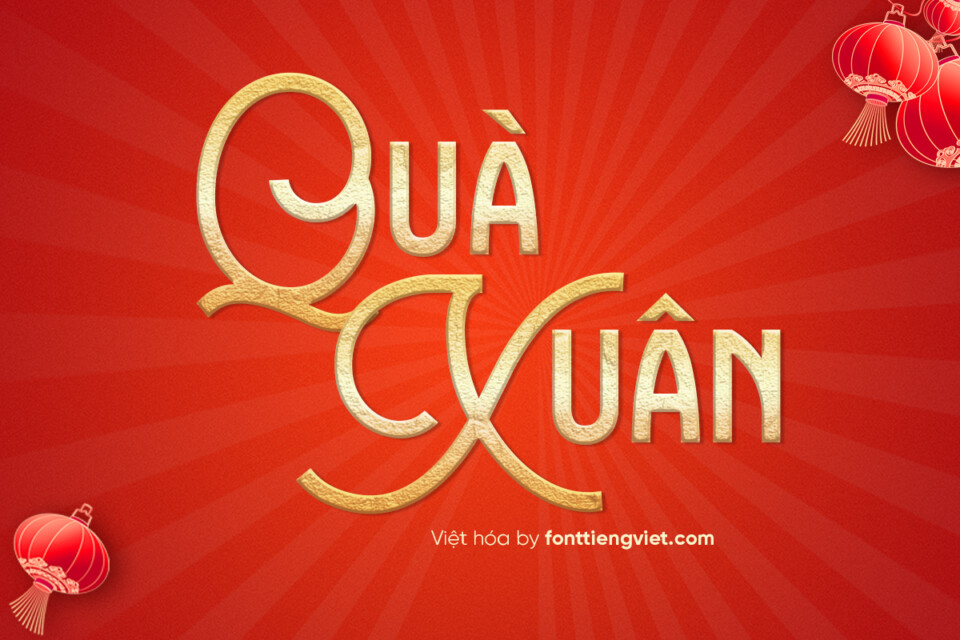
Font Việt hóa 1FTV VIP Colgneries – Font tết: Sự lựa chọn hoàn hảo cho thiết kế Xuân rạng rỡ
Chào mừng bạn đến với thế giới sáng tạo nơi những nét chữ truyền tải linh hồn của mùa xuân. Trong không khí hân hoan chuẩn bị đón năm mới, việc tìm kiếm một bộ Font Miễn Phí chất lượng để phục vụ cho các dự án thiết kế là điều vô cùng cần thiết. Font Việt hóa 1FTV VIP Colgneries – Font tết nổi lên như một ứng cử viên sáng giá nhất hiện nay. Đây là bộ font mang phong cách hiện đại pha lẫn chút cổ điển, rất phù hợp để làm nổi bật các thông điệp chúc mừng năm mới. Với sự tỉ mỉ trong quá trình việt hóa, bộ font này đảm bảo hiển thị hoàn hảo các dấu tiếng Việt mà không xảy ra lỗi kỹ thuật, giúp các bạn học sinh và giáo viên dễ dàng tạo ra những tấm thiệp hay bảng tin trường học đầy ấn tượng và chuyên nghiệp.
Khám phá vẻ đẹp độc đáo của Font Việt hóa 1FTV VIP Colgneries – Font tết
Bộ font này không chỉ là những ký tự vô hồn mà là cả một nghệ thuật sắp đặt. Font Việt hóa 1FTV VIP Colgneries – Font tết sở hữu những đường nét thanh mảnh nhưng vô cùng chắc chắn, gợi lên hình ảnh của những cành mai cành đào đang đua nhau khoe sắc. Khi sử dụng bộ chữ này, người thiết kế có thể dễ dàng cảm nhận được sự tinh tế trong từng nét thanh nét đậm. Điều này giúp bài viết hoặc ấn phẩm đồ họa trở nên thanh thoát và dễ tiếp cận hơn với người xem. Đặc biệt, cấu trúc của font được tối ưu hóa cho các tiêu đề lớn, tạo điểm nhấn mạnh mẽ ngay từ cái nhìn đầu tiên trên các banner quảng cáo tết hoặc các tiêu đề bài giảng điện tử cho học sinh.
Ứng dụng đa dạng trong thiết kế đồ họa sự kiện
Sự linh hoạt của Font Việt hóa 1FTV VIP Colgneries – Font tết cho phép nó xuất hiện ở nhiều định dạng khác nhau. Bạn có thể dùng font này để thiết kế bao lì mừng tuổi, các câu đối đỏ hiện đại hoặc thậm chí là menu cho các bữa tiệc tất niên. Với phong cách sang trọng, font chữ giúp nâng tầm giá trị thẩm mỹ của sản phẩm. Đối với các bạn học sinh, việc sử dụng font chữ này trong các bài thuyết trình về chủ đề Tết Nguyên Đán sẽ giúp nội dung trở nên sinh động và thu hút thầy cô giáo hơn. Khả năng kết hợp linh hoạt với các tông màu đỏ và vàng – màu chủ đạo của ngày Tết – khiến bộ font trở thành một công cụ đắc lực không thể thiếu trong kho tài nguyên của bất kỳ ai yêu thích thiết kế.
Lời kết về giá trị của bộ font trong mùa lễ hội
Việc sở hữu một bộ chữ đẹp và đúng chủ đề chính là chìa khóa để tạo nên sự thành công cho các dự án truyền thông dịp cuối năm. Font Việt hóa 1FTV VIP Colgneries – Font tết thực sự là một món quà ý nghĩa dành cho cộng đồng yêu thiết kế tại Việt Nam. Nó không chỉ giúp giải quyết vấn đề hiển thị ngôn ngữ mà còn mang lại cảm hứng sáng tạo vô tận. Hy vọng rằng với những chia sẻ trên, bạn sẽ có thêm một sự lựa chọn tuyệt vời để trang trí cho không gian số của mình thêm phần rực rỡ. Đừng quên truy cập vào Font Miễn Phí, Font Việt Hóa, Font Việt hóa 1FTV VIP Colgneries – Font tết để cập nhật thêm nhiều bộ chữ độc đáo khác cho bộ sưu tập cá nhân của mình nhé.